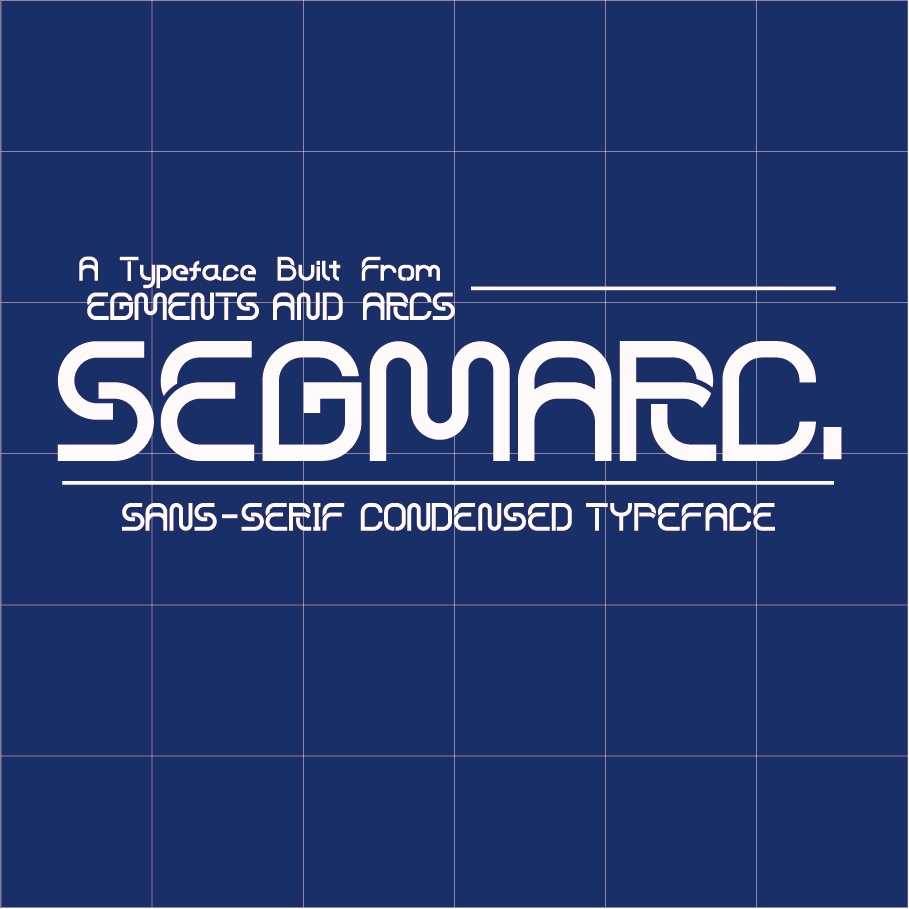
SEGMARC Typeface|フォント [Free / Donation]
卒業制作にて制作した、オリジナルの欧文フォントです。 幾何学的な印象を持ちながらも視認性を保ち、 ロゴデザインやポスター、UI、映像テロップなど、 インパクトを求められる場面での使用を想定して設計されています。 制作展での展示体験をきっかけに、本フォントを公開いたしました。 ぜひ皆さまのデザインワークにご活用いただけましたら幸いです。 💰 価格について 無料版:どなたでも自由にお使いいただけます。 投げ銭版:内容は無料版と同一ですが、制作活動を応援いただける方はこちらからご支援いただけます。今後の制作の励みになります。 📦 フォント仕様 ウェイト:Regular 文字種: - アルファベット(A–Z / a–z) - 数字(0–9) - 一部記号 ※収録記号はサンプル画像をご確認ください。 対応言語:Basic Latin フォーマット:OpenType (.otf) ペアカーニング調整済み 🖥 Webフォント利用について WOFF等への変換および、Webフォントとしての使用は可能です。 ただし、フォントファイル自体がダウンロード可能な状態での設置は禁止いたします。 ✅ 使用できる範囲 【OK】 個人・商用問わず、各種デザイン制作物への使用 (印刷物、Web、映像、ゲーム、アプリ等) 収益化されたSNSやYouTube等での使用 文字のアウトライン化・加工を行った上での ロゴデザインやグラフィック制作への使用 【NG】 フォントファイルの二次配布、転売、譲渡 フォントを改変して「自作フォント」として配布・販売する行為 本フォントを使用したロゴ等の商標登録 (フォントの形状を独占することになるため) 特定の個人・団体を誹謗中傷する目的、 または公序良俗に反するコンテンツでの使用 その他 著作権について 本フォントの著作権は放棄しておりません。 すべての権利は作者に帰属します。 商用利用の際のご連絡について 使用報告は任意ですが、ご連絡いただけますと非常に励みになります。 「こんなものに使ったよ」といったURLや画像など、ぜひお知らせください。 免責事項 本フォントの使用によって生じたいかなるトラブル・損害について、 作者は一切の責任を負いません。 💡 展示に来てくれた方へ 制作展にてQRコードからお越しいただいた皆さま、 この度はアクセスいただきありがとうございます!